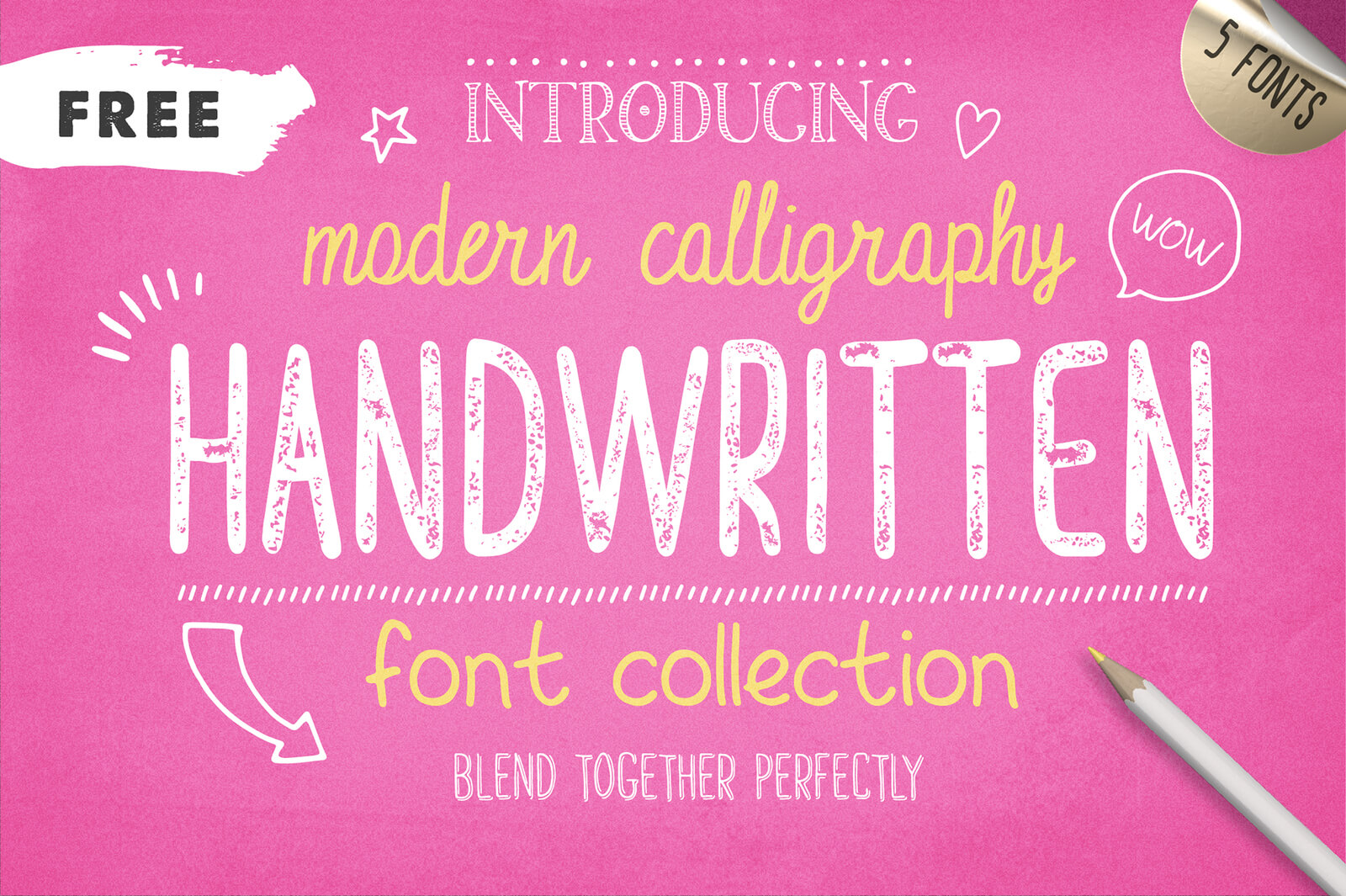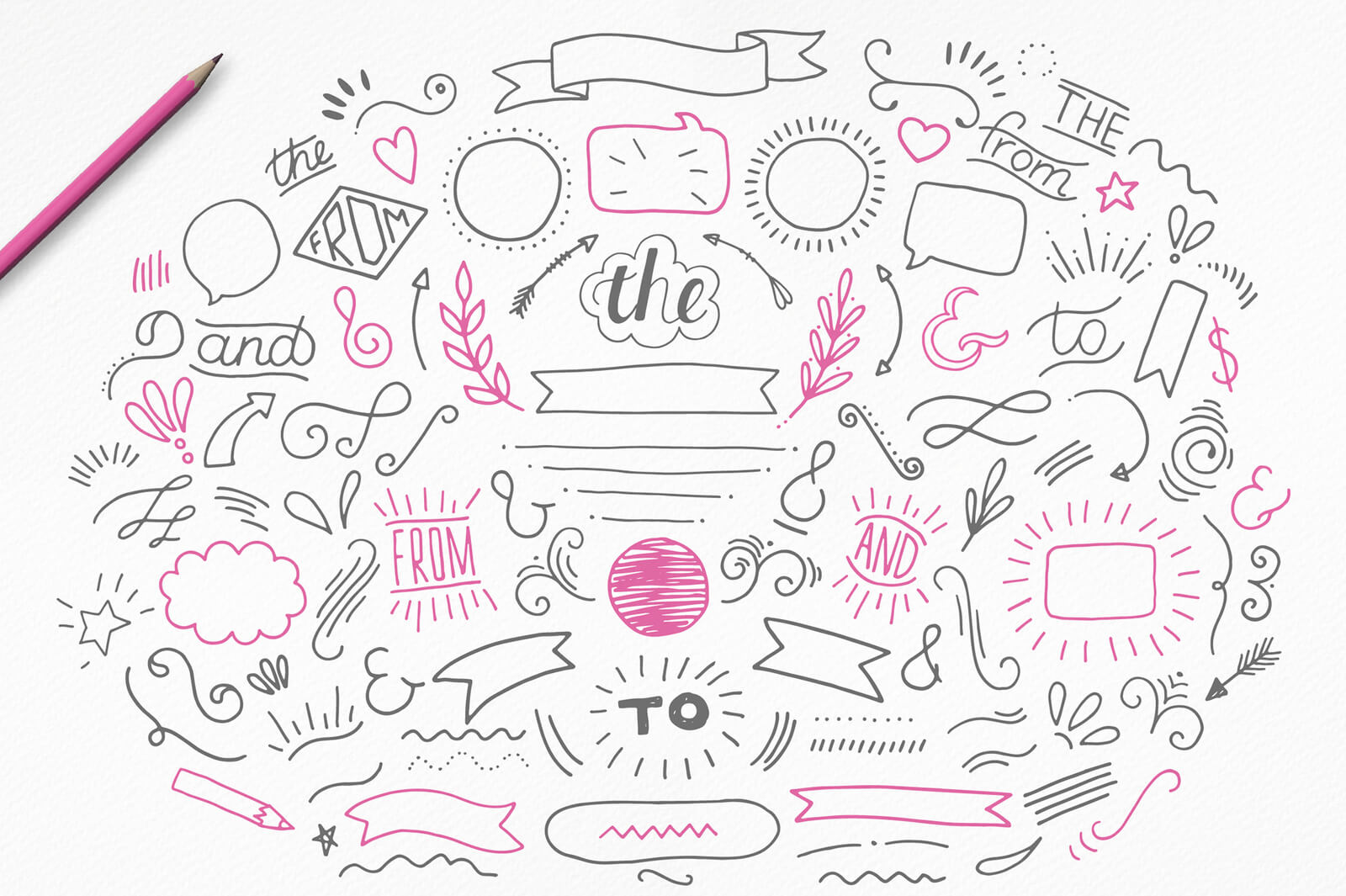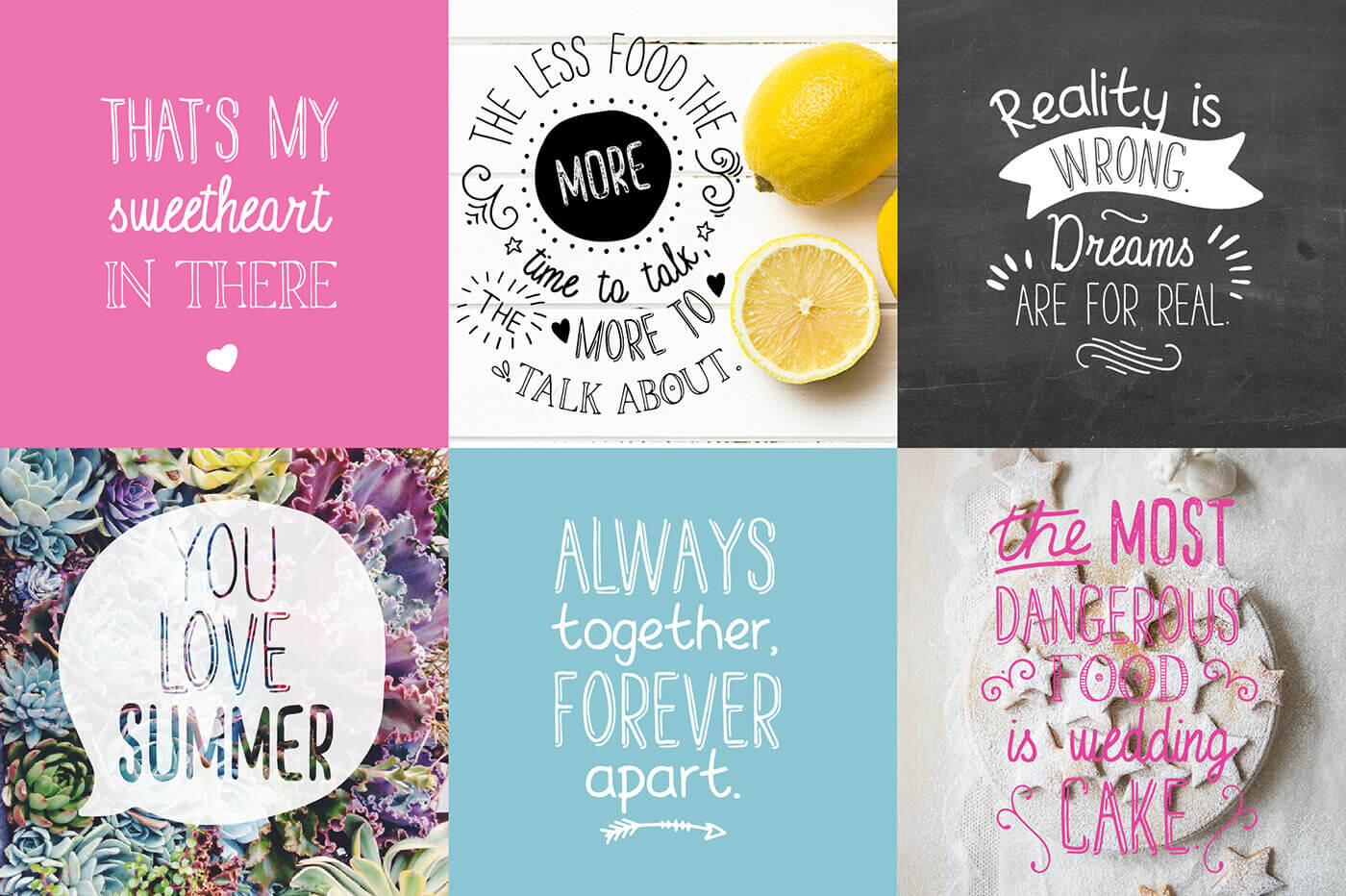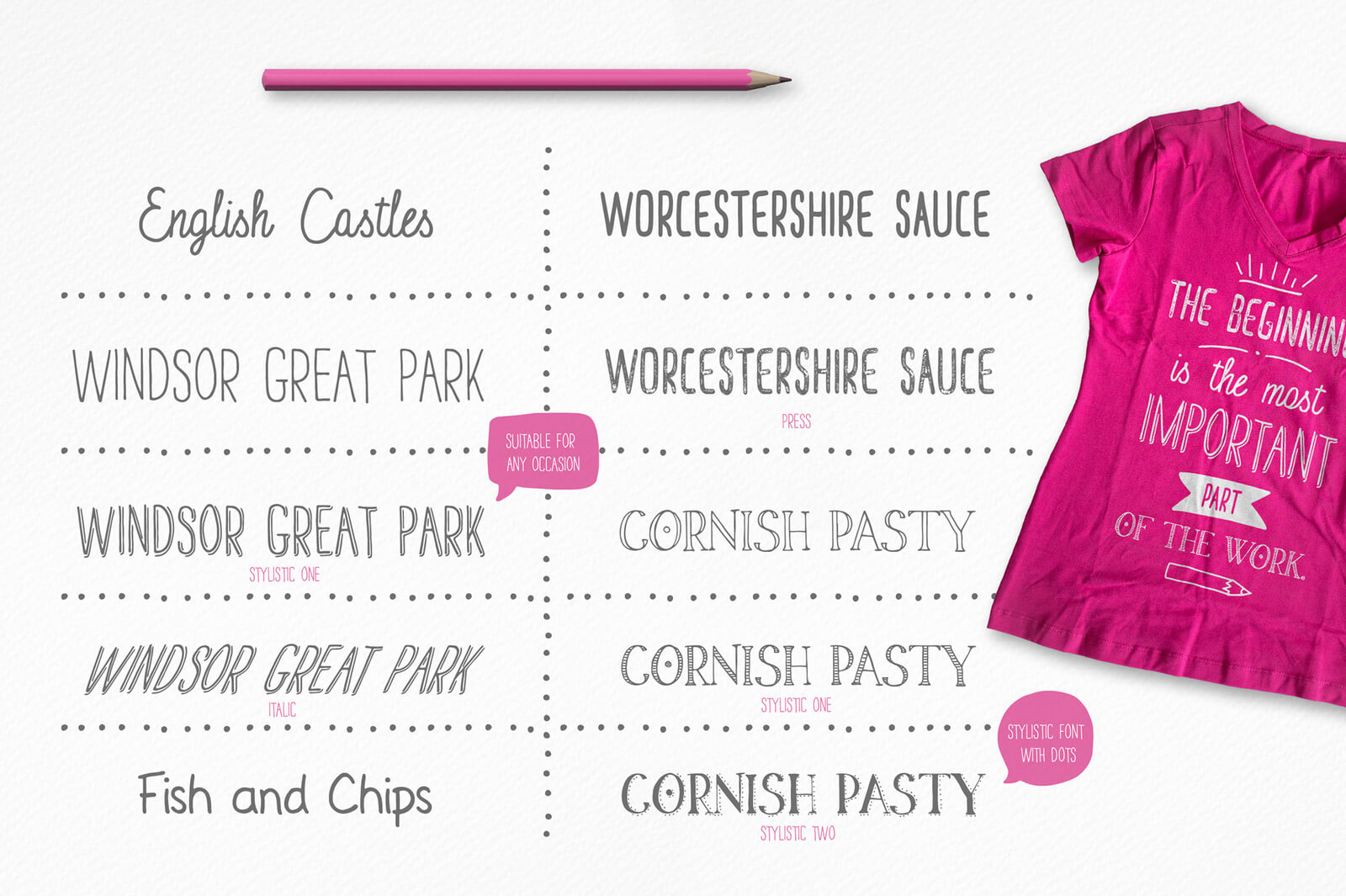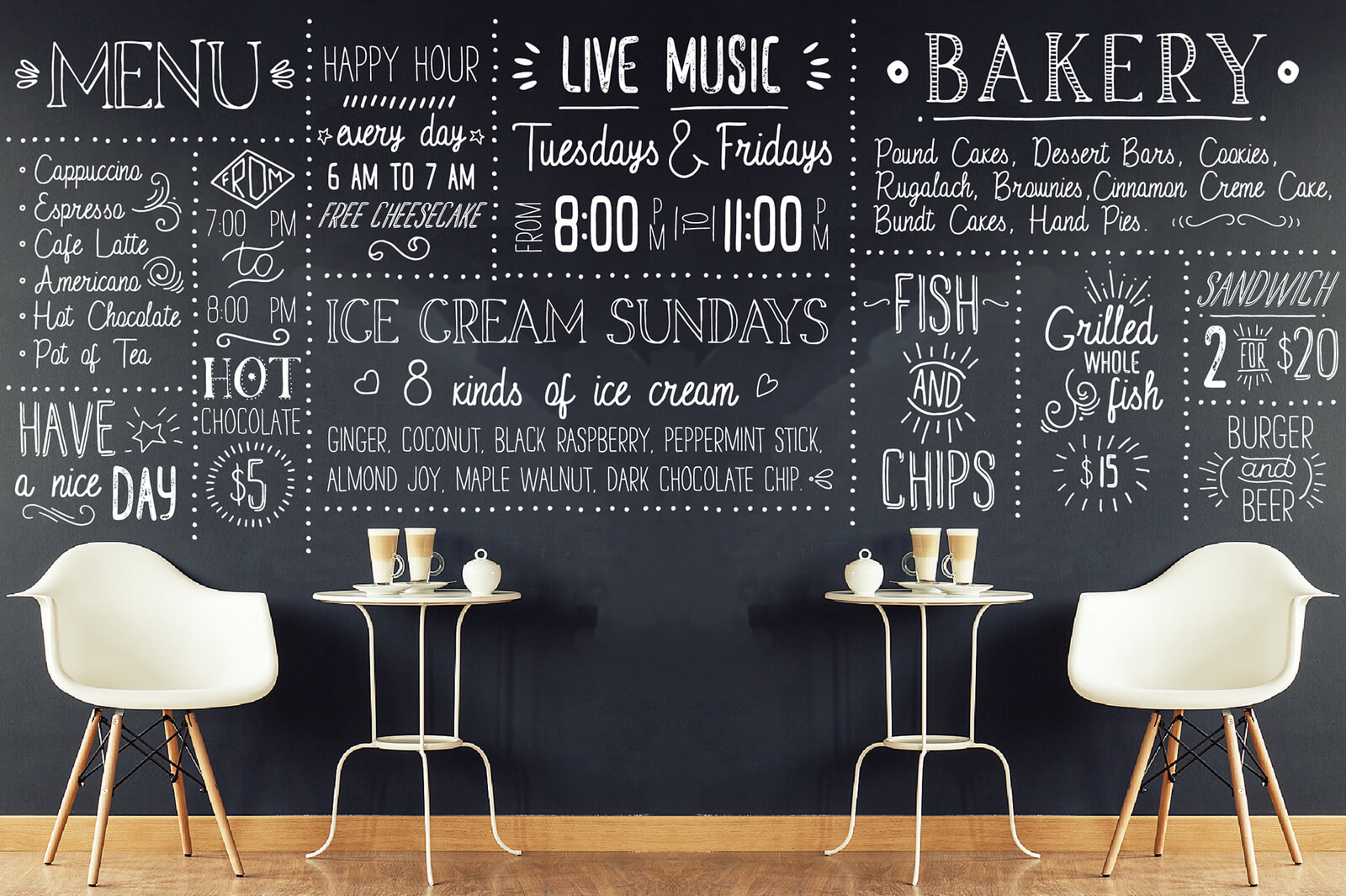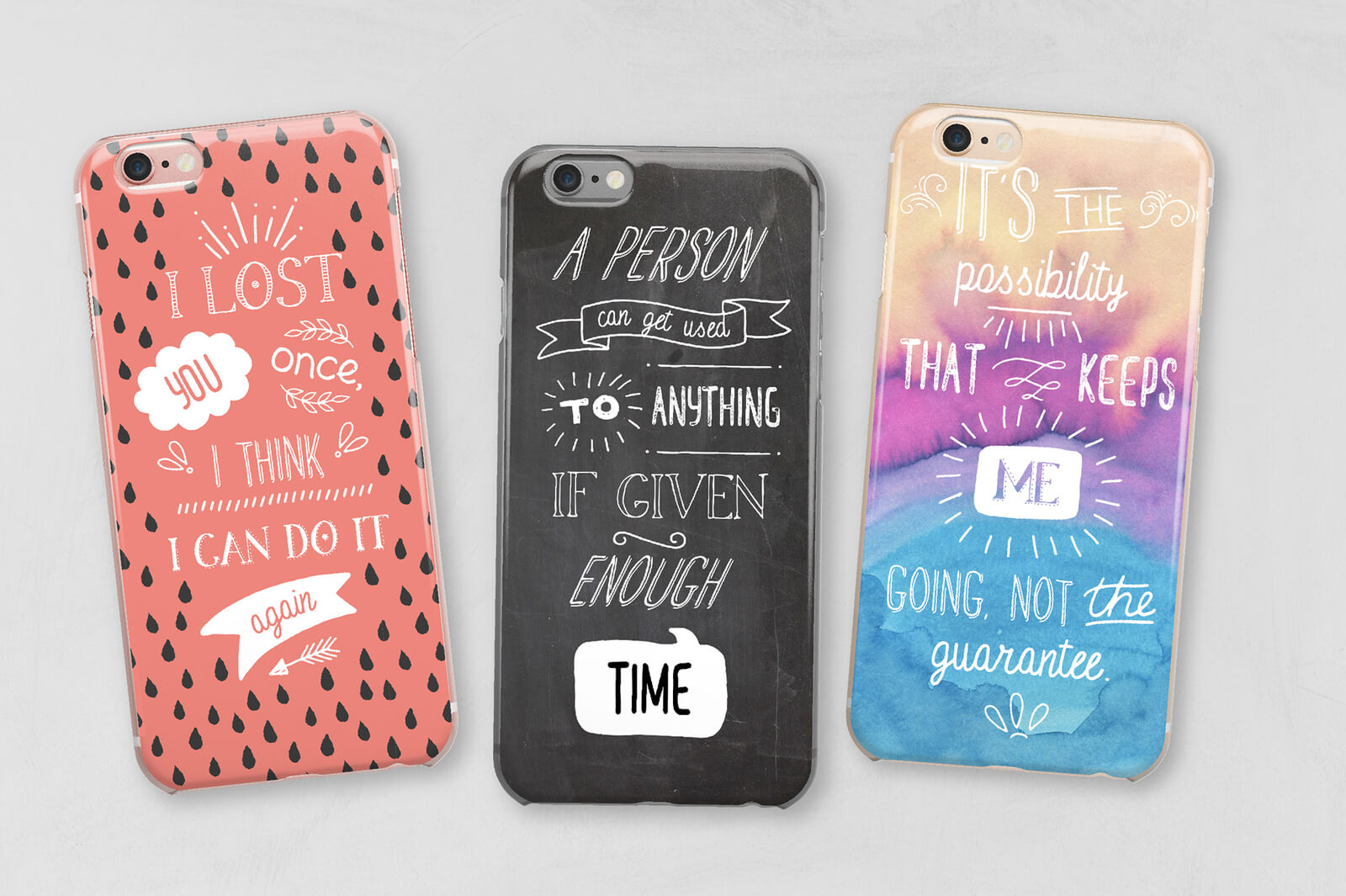
Коллекция рукописных шрифтов (Латиница)
Это 5 рукописных шрифтов и 5 альтернативных стилей, которые идеально сочетаются друг с другом и отлично подходят для любого вашего проекта. В пакет входят бесплатные декоративные элементы, специально разработанные для этих шрифтов.